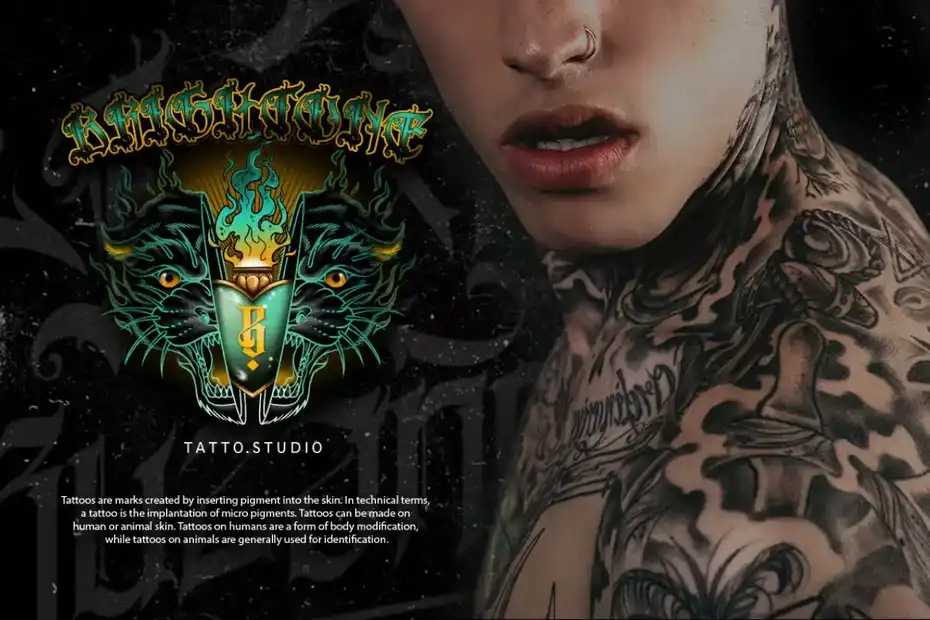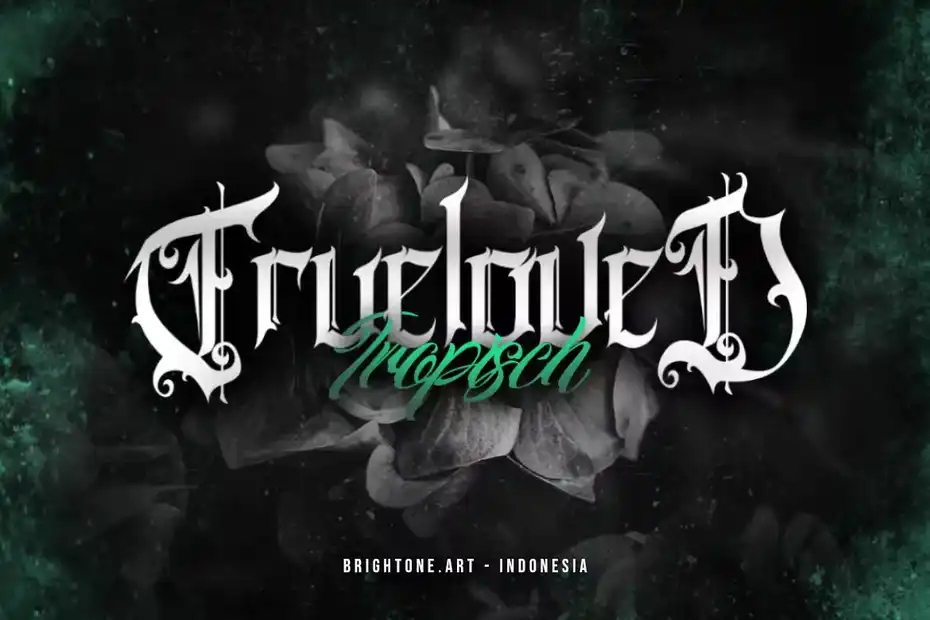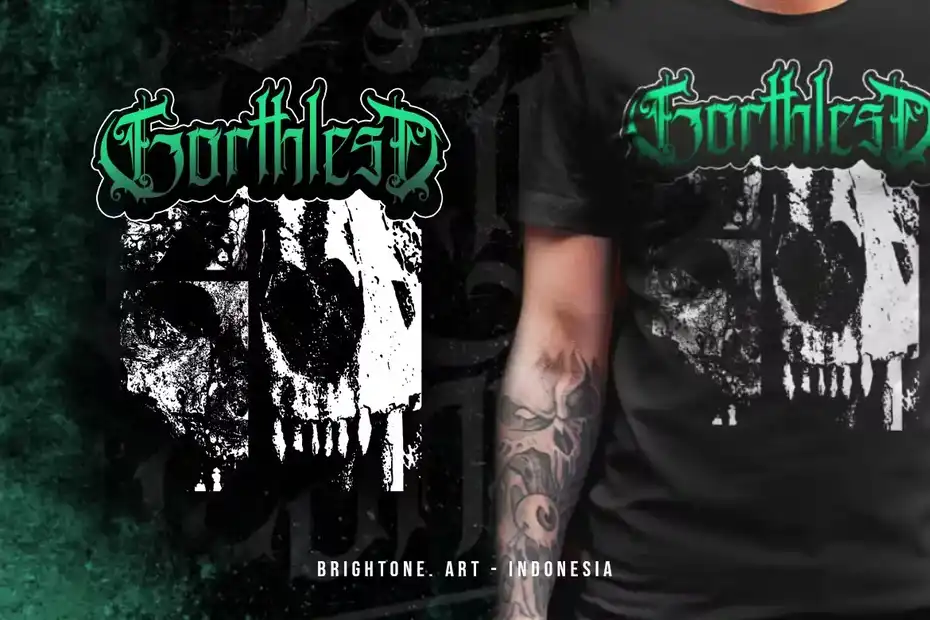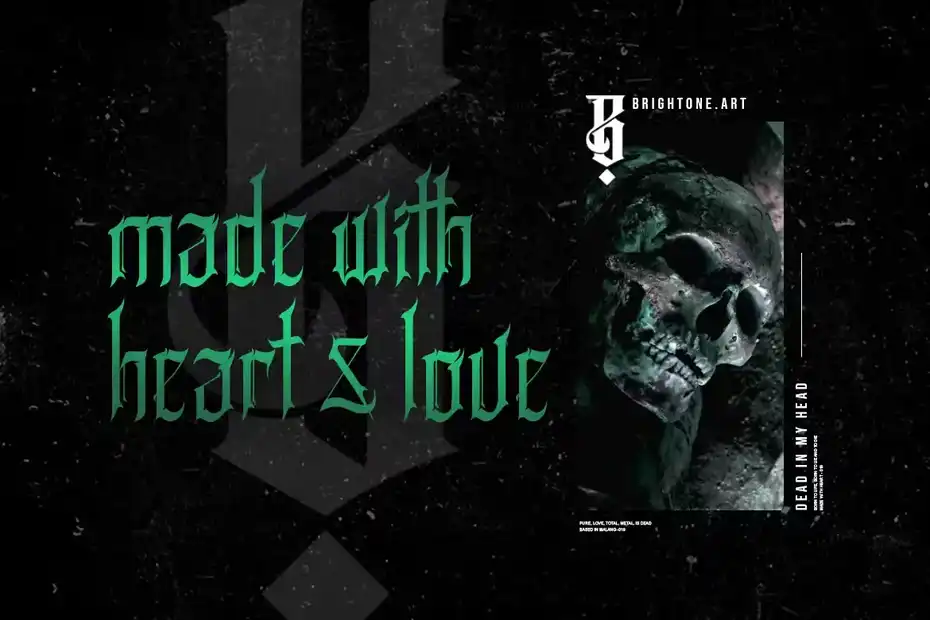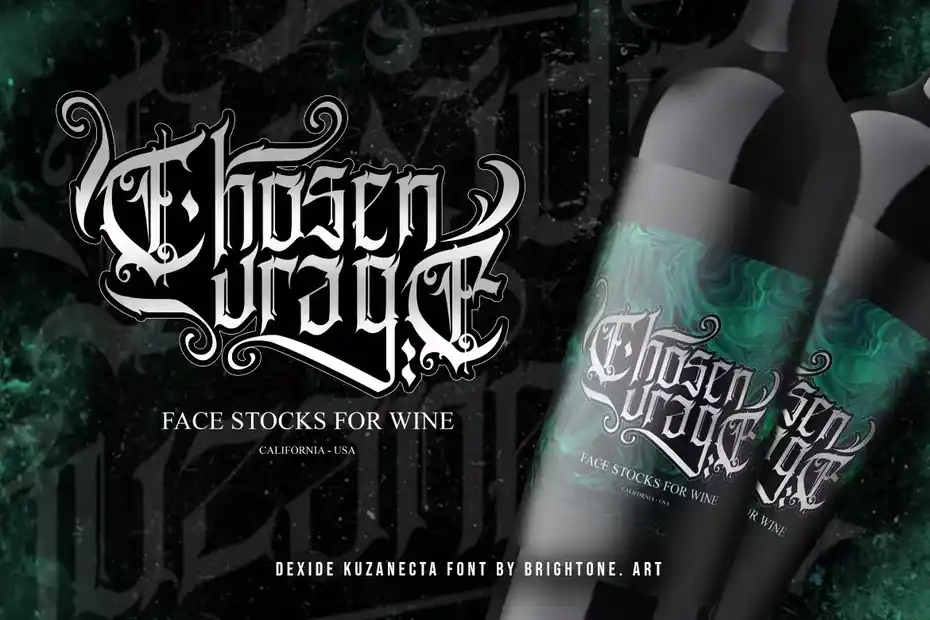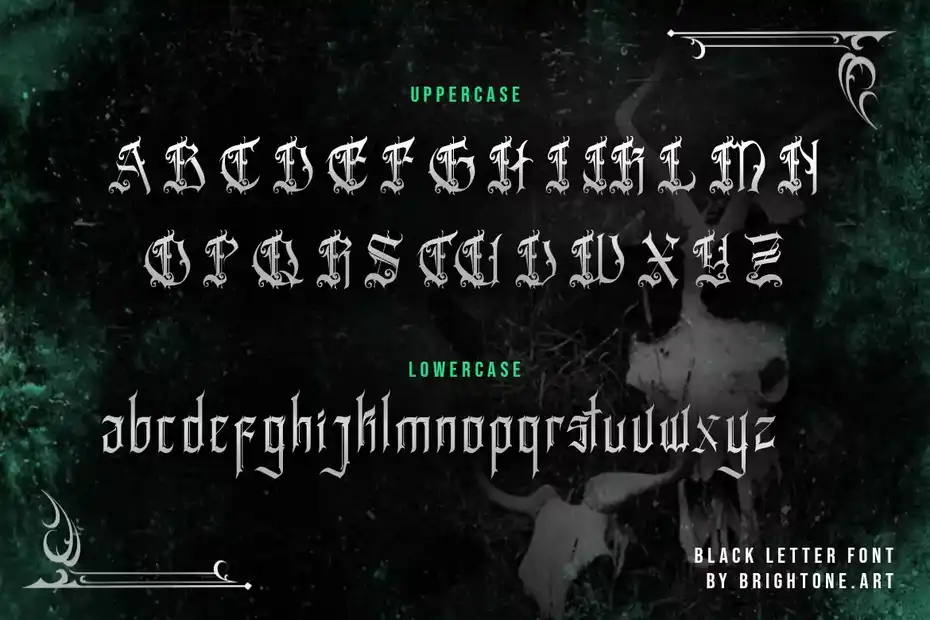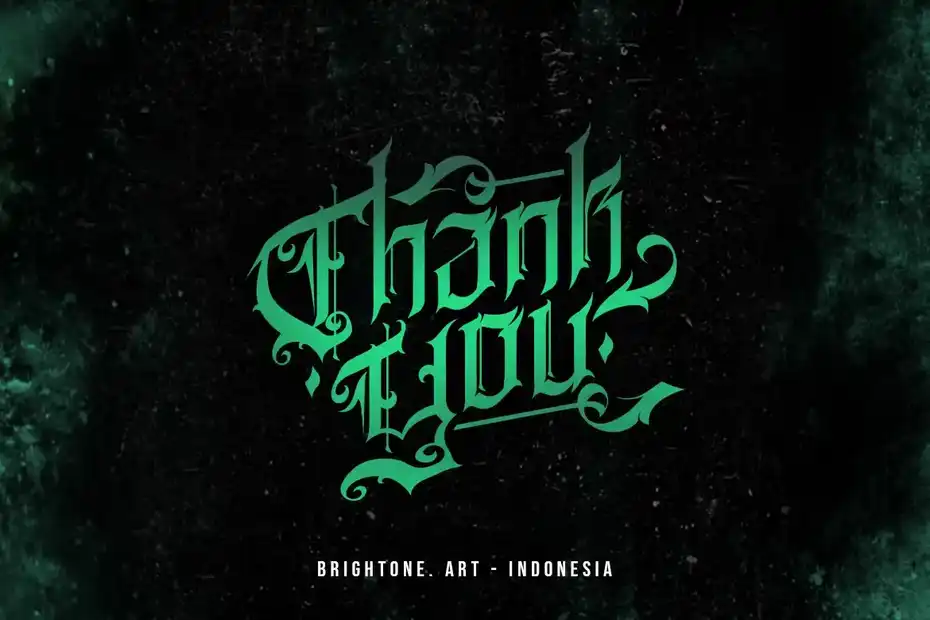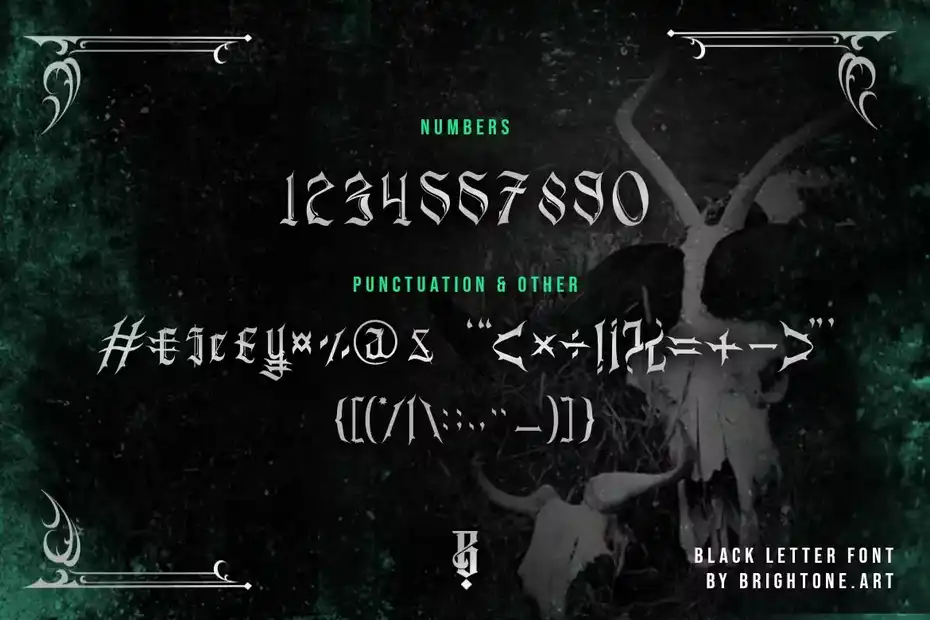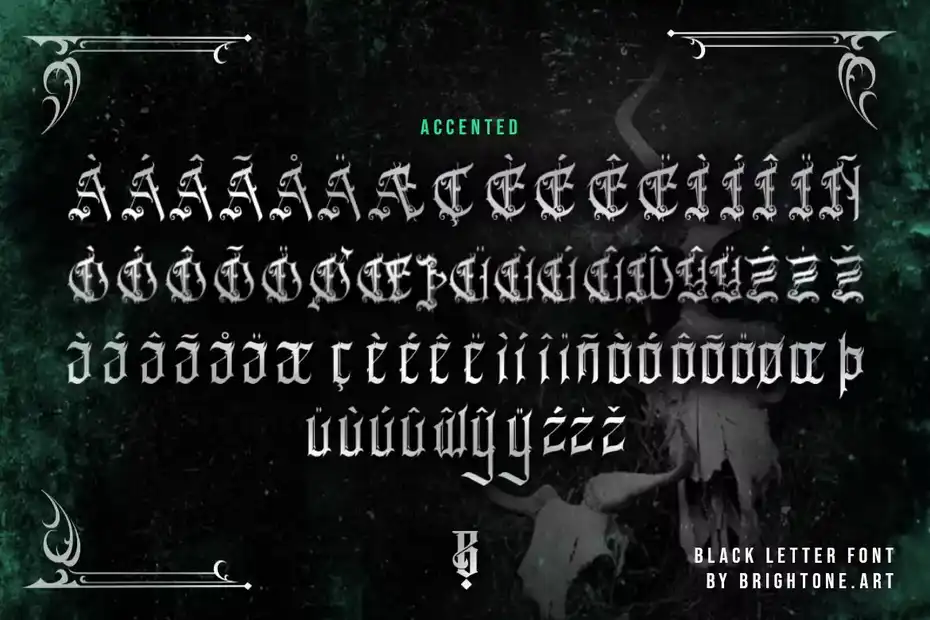
دانلود فونت انگلیسی تاتو Espada Del Destino – Gothic Type Font
فونت انگلیسی تاتو Espada Del Destino – Gothic Type Font : این مجموعه شامل یک فونت انگلیسی کلاسیک است که برای تاتو، برندینگ، لوگو، تیشرت و غیره مناسب میباشد.